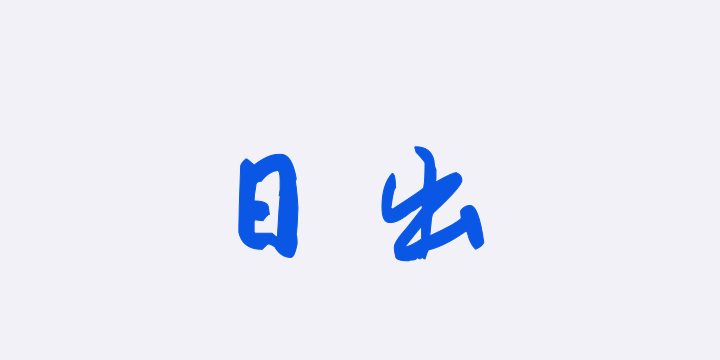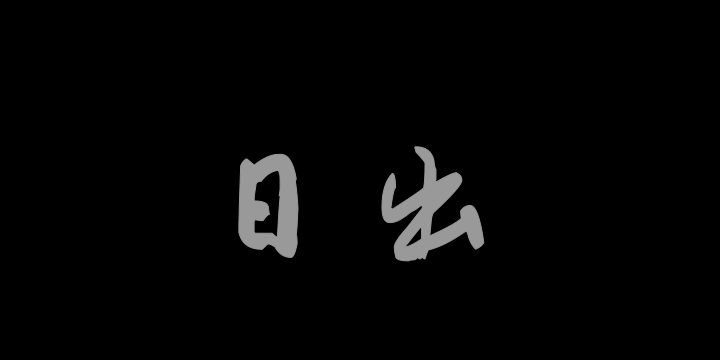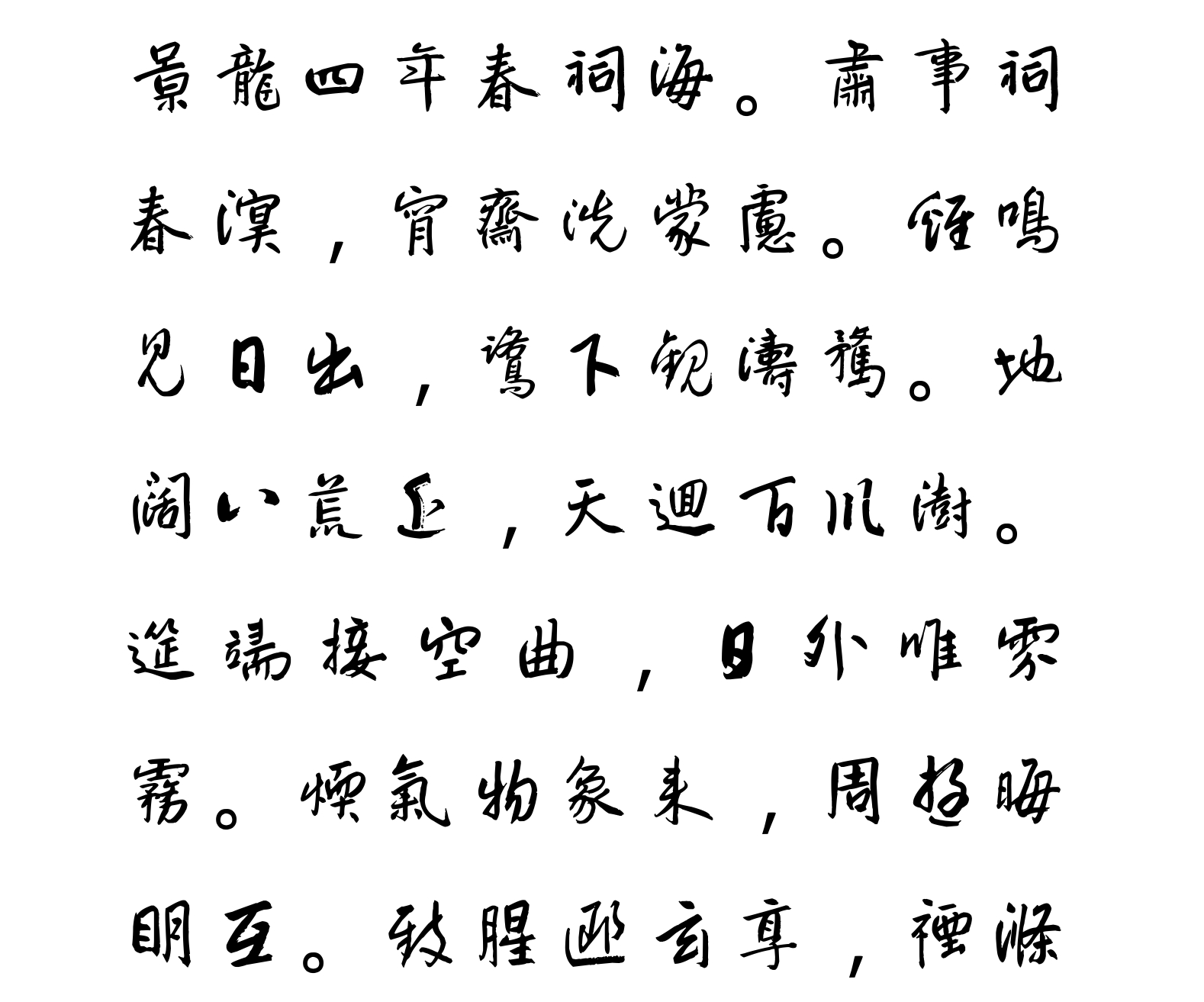
字体全名: 汉标八大山人宋之问诗
字体简介: 1、下载须知:汉标八大山人宋之问诗字库非标准GB2312字库。本字库只包含了真迹书法原稿中的部分字体。字库中字数的多少取决于原稿的字数的多少。你可以通过该字详情页上面的输入框如果有明白的请先联系字觅客服咨询。 2、简介:本字库由“汉标字库”根据收集到的真迹书法图片,并运用抠图、处理背景图、运用造字软件书法作品调整字体笔画基本位置,合理布局,提高清晰度,去除笔画边缘毛刺及脏点,纠正错别字,均衡整体文字的大小,再次创作而制作成现代字库,再将原版汉字逐字编码代入模板,在制作成小字库。这样做有助于中国古代书法艺术的传承具有划时代意义,并且通过把古代名家书法真迹制作成现代字库,让更多书法爱好者能够通过电脑打字使用,真正感受到古代名家书法之美。并且也可以在各种场景下应用。 3、古代真迹的书法家有:王羲之、王献之、欧阳询、颜真卿、柳公权、赵孟頫、苏轼、黄庭坚、米芾、蔡襄等